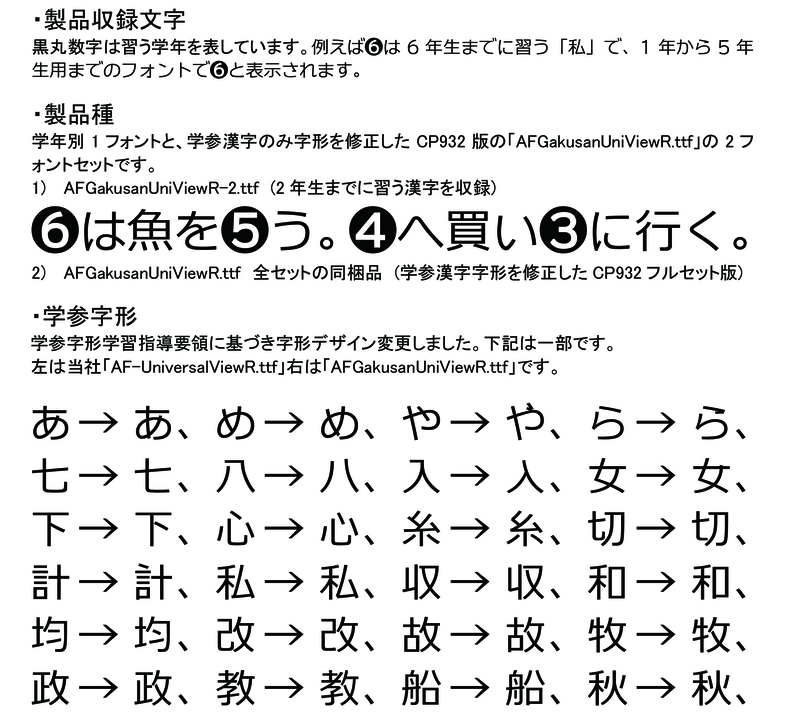
可読性を重視したユニバーサルビューのレギュラーをベースに文部科学省学習指導要領の字形を再現、他に類を見ない学年別学参フォントをご案内します。ドリル等教材用はもちろん児童を対象とした配布資料作成に最適です。その対象学年までに習う文字を収録したフォントと学参漢字のみ字形を修正したCP932フルセット版の2書体セットです。
学参 小学2年生用R